#コンパス 戦闘摂理解析システム
「#コンパス 戦闘摂理解析システム」は基本料金無料のiOS、Android対応のリアルタイムオンライン対戦ゲーム。運営・開発はNHN PlayArt株式会社と株式会社ドワンゴ。
「1バトル3分間」として仲間とチームを組んで他プレイヤーのチームと3対3のバトルが行われる。ステージに配置された拠点を奪い合い、スキルカードを集めて、組み合わせによる多彩な戦略で最強のデッキを作り、対戦に備えることができるアクションゲーム。
東京ゲームショー2018の#コンパスブース
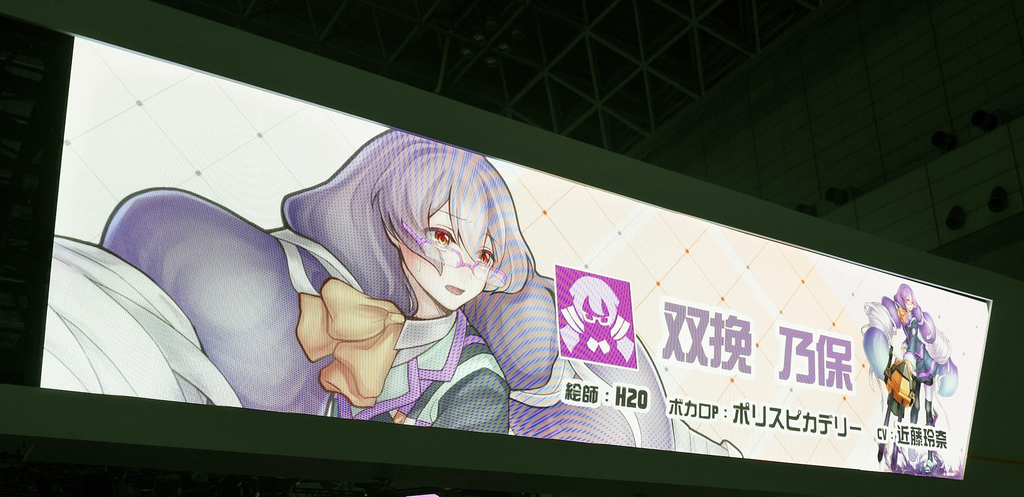
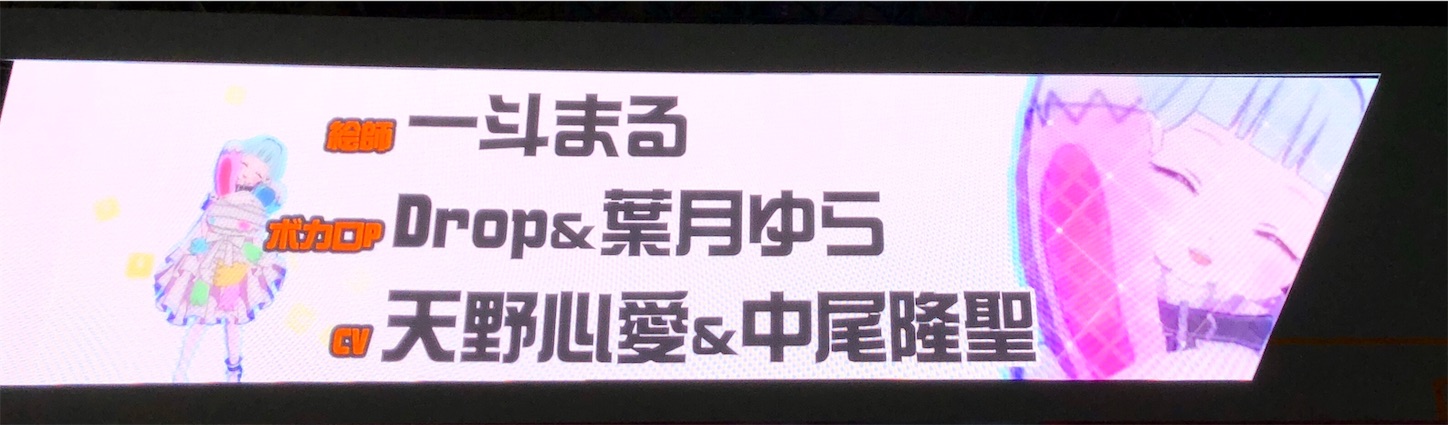
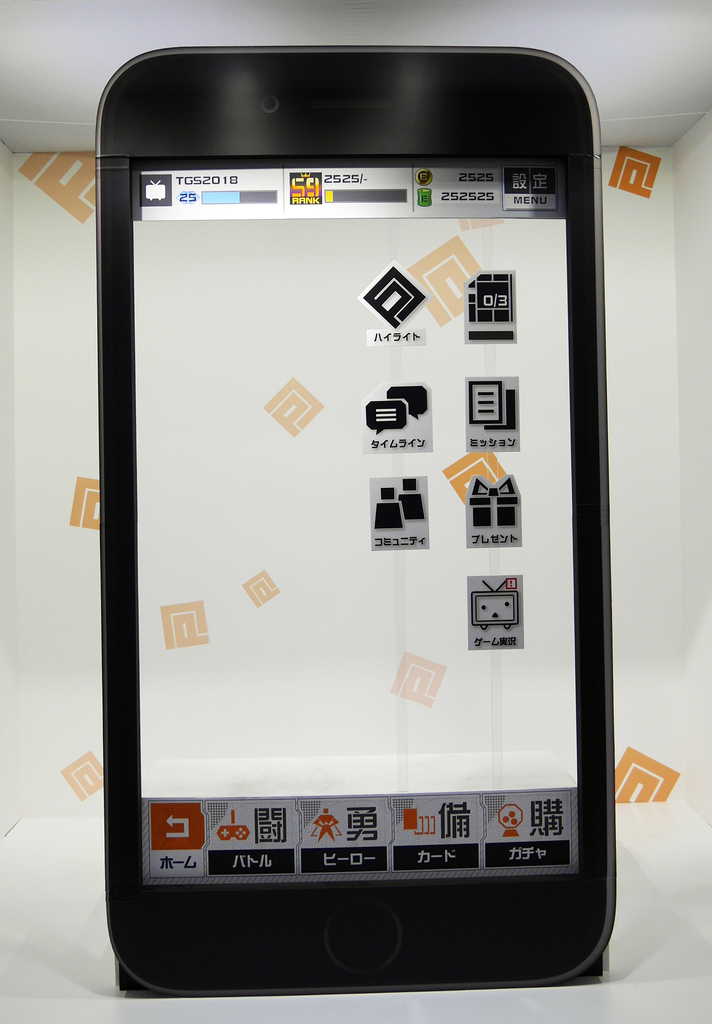
「#コンパス 戦闘摂理解析システム」にダイナフォントの綜藝体が採用
綜藝体の使用理由として少し角張った四角く、ミリタリー色のある文字デザインであることからダイナフォントの綜藝体が使用されたのこと。デジタルミリタリー感のある綜藝体や綜藝体に似た華藝体はよくゲームで使用されているのを見かける。
▼ダイナフォントの綜藝体が使用されているゲーム画面。
文房具屋さん大賞のタイトルに綜藝体が使用されている。
綜藝体
通常のゴシック体よりも太く正方な字形で、文字内の余白部分を均等化したデザインフォント。まっすぐ伸びた線の曲がりやハネの先端部分をややカーブさせているのが特徴。